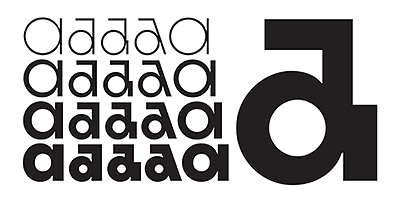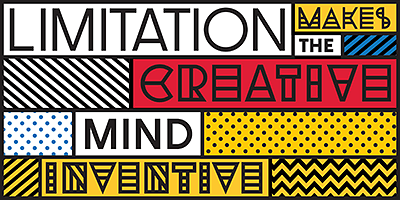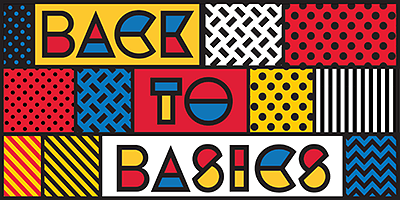
UTOPIAN은 Bauhaus, DeStijl과 Art Deco의 영향을 받은 원색 및 순수 기하학적인 모양을 기반으로 제작된 컬러 글꼴 패밀리입니다. 제품의 순수한 모양과 원색은 모듈식 명령과 그리드에 영감을 받아 모든 요소가 색상이 조화를 이루는 완벽한 환경을 조성합니다. 반면에 DYSTOPIAN 흑백 제품군은 UTOPIAN과는 외관 및 구조가 매우 유사하지만 어두운 모양과 느낌으로 서로 다른 의미를 가집니다. 두 서체는 미래에 대한 의견 차이와 잠재적 결과를 반영하고 있습니다.